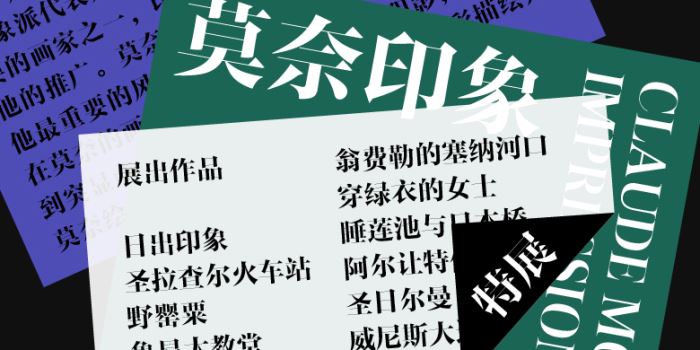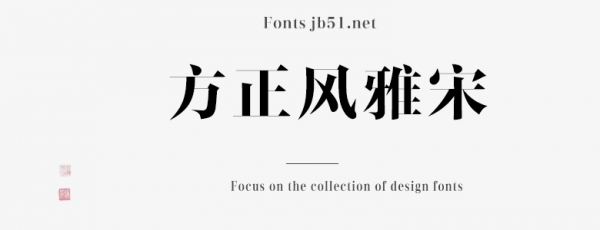
方正風(fēng)雅宋家族由方正字庫朱志偉,蘇士鵬,烏新麗設(shè)計(jì)師出品的藝術(shù)字體,字體筆鋒銳化挺拔,去掉了橫畫起筆處的飾角,撇捺的起收形態(tài)也簡(jiǎn)化取直,適合應(yīng)用于藝術(shù)設(shè)計(jì)、平面宣傳設(shè)計(jì)、網(wǎng)頁設(shè)計(jì),書法等領(lǐng)域。
方正風(fēng)雅宋家族是以方正雅宋為基礎(chǔ)設(shè)計(jì)的。方正雅宋是為了滿足報(bào)刊和書籍的正文排版,而方正風(fēng)雅宋則是為了滿足更加現(xiàn)代、時(shí)尚的標(biāo)題用字。方正風(fēng)雅宋的筆鋒銳化挺拔,去掉了橫畫起筆處的飾角,撇捺的起收形態(tài)也簡(jiǎn)化取直,刻意拉大了橫豎筆畫的粗細(xì)反差,產(chǎn)生強(qiáng)烈對(duì)比。這些特征使它更為簡(jiǎn)潔現(xiàn)代,具有強(qiáng)烈的視覺張力。
適用于報(bào)紙、雜志和書籍的標(biāo)題,以及廣告、標(biāo)志和產(chǎn)品包裝的設(shè)計(jì)。